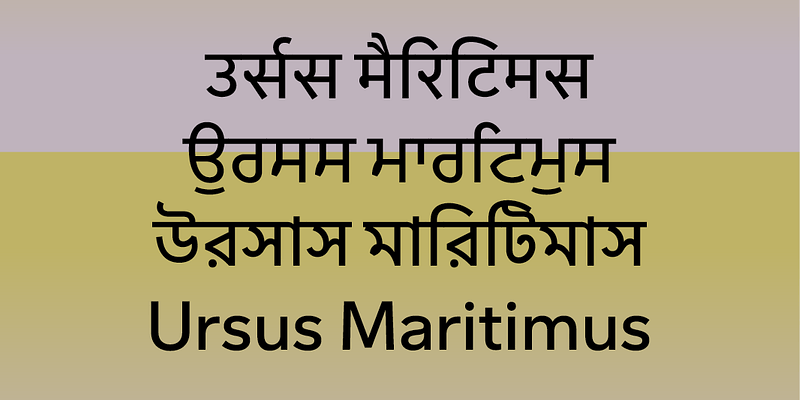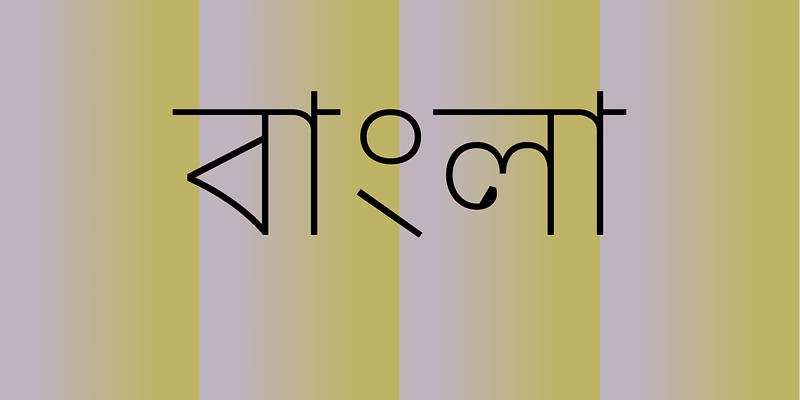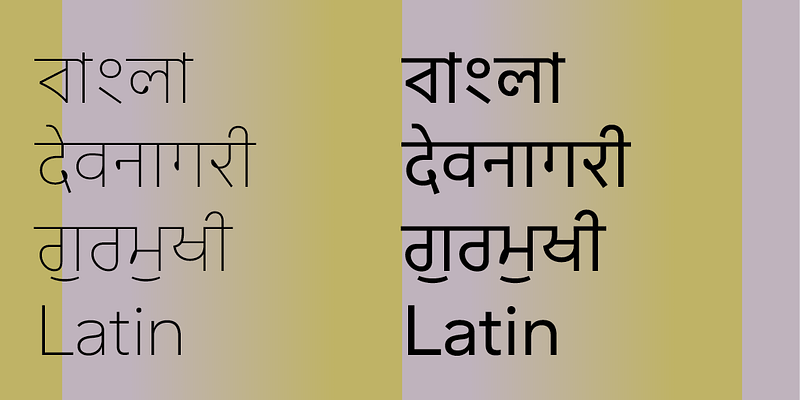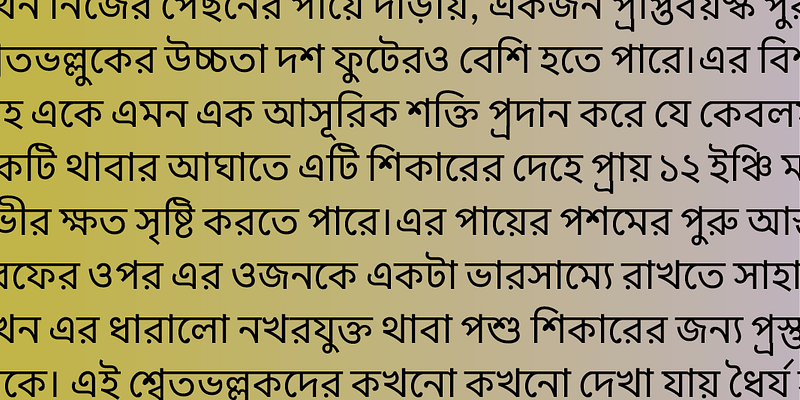
Sarvatrik 提供了一组强大的粗细以及跨孟加拉语、Devanagari、果鲁穆奇语和拉丁语的语言支持 - 随后还将提供更多的印度文字体。这是一个实用的选择,在大尺寸和小尺寸上都表现良好,但又不失其友好、开放的个性。拉丁语版本与孟加拉语、Devanagari 和果鲁穆奇语无缝对接,使其成为多语言品牌化或在多个市场运营业务的公司的绝佳选择。
书写系统:拉丁语、Devanagari、孟加拉语、果鲁穆奇语
Universal Thirst 是一家专门制作印度文和拉丁文字体的字体开发公司。这家公司由设计师和工程师二人组 Gunnar Vilhjálmsson 与 Kalapi Gajjar 于 2016 年创立,他们利用各自对比鲜明的视觉传承,提供有关字体的独特的双重视角。
Universal Thirst 为各种规模的公司制作定制字体。我们的全球视野使我们成为各个业务遍及全球的品牌(尤其是在南亚开展业务的品牌)的宝贵的设计合作伙伴。